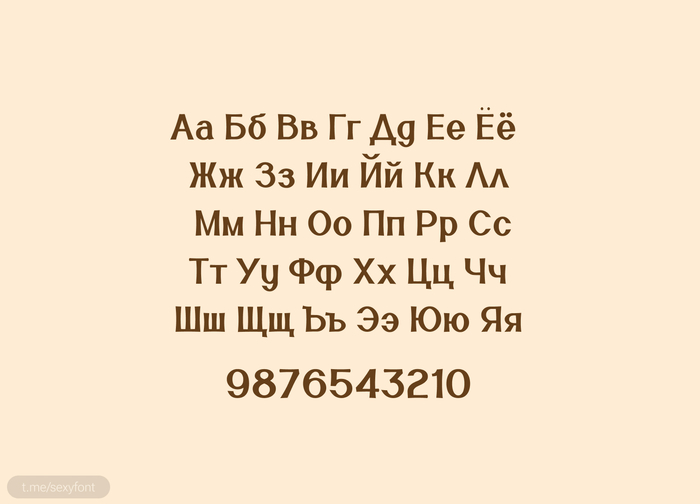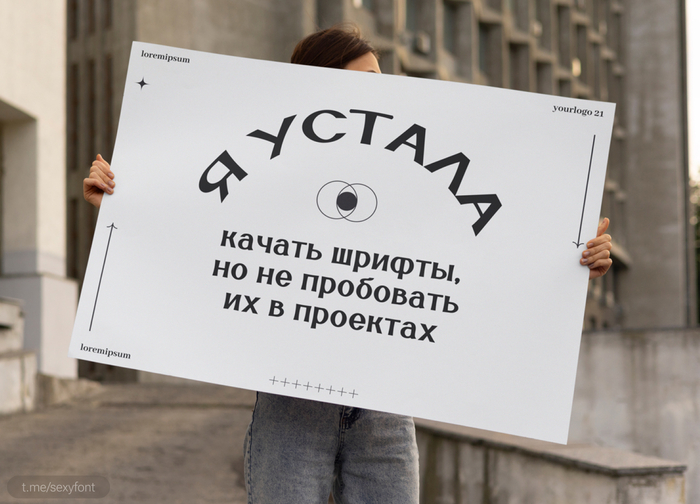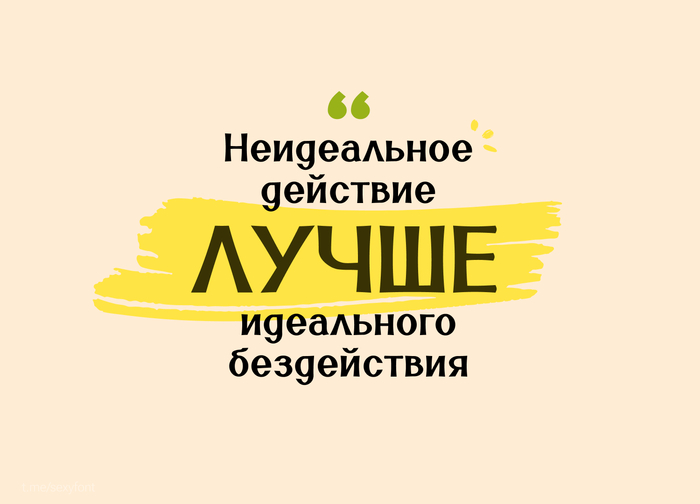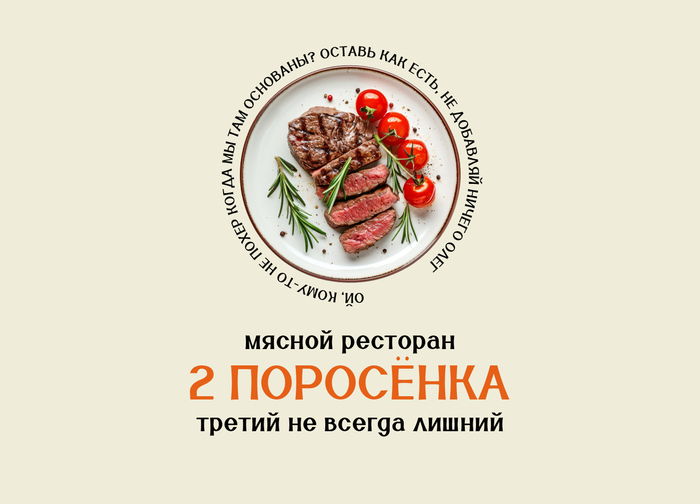
Шрифт дудка
Полностью бесплатный кириллический шрифт. Может не супер выразительный, но зато неплохо читаемый) В меру декоративный. Есть целых 6 начертаний
Автор: Дмитрий Антонов